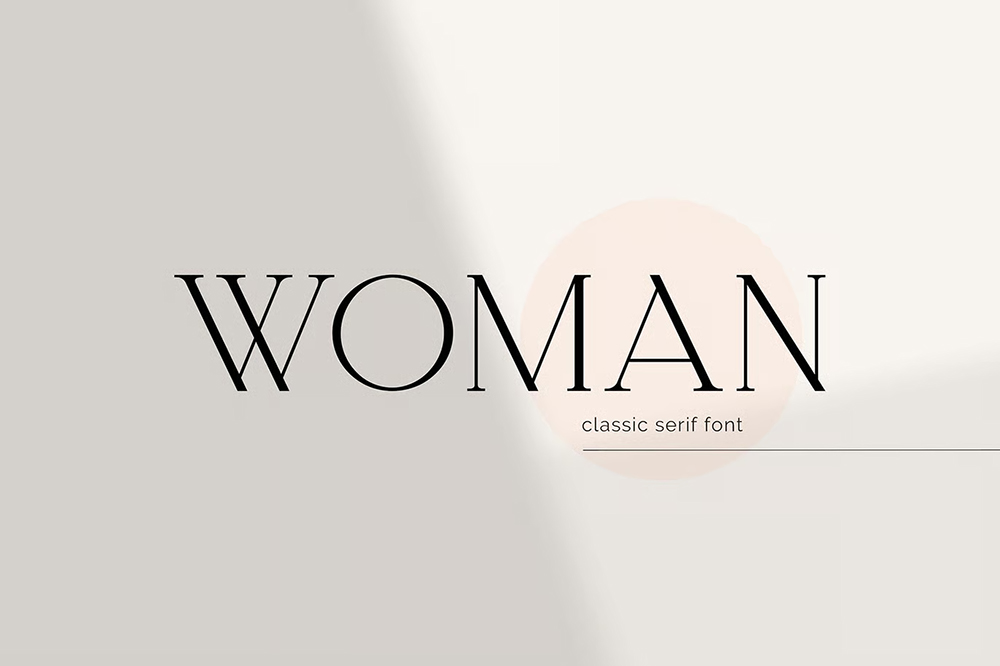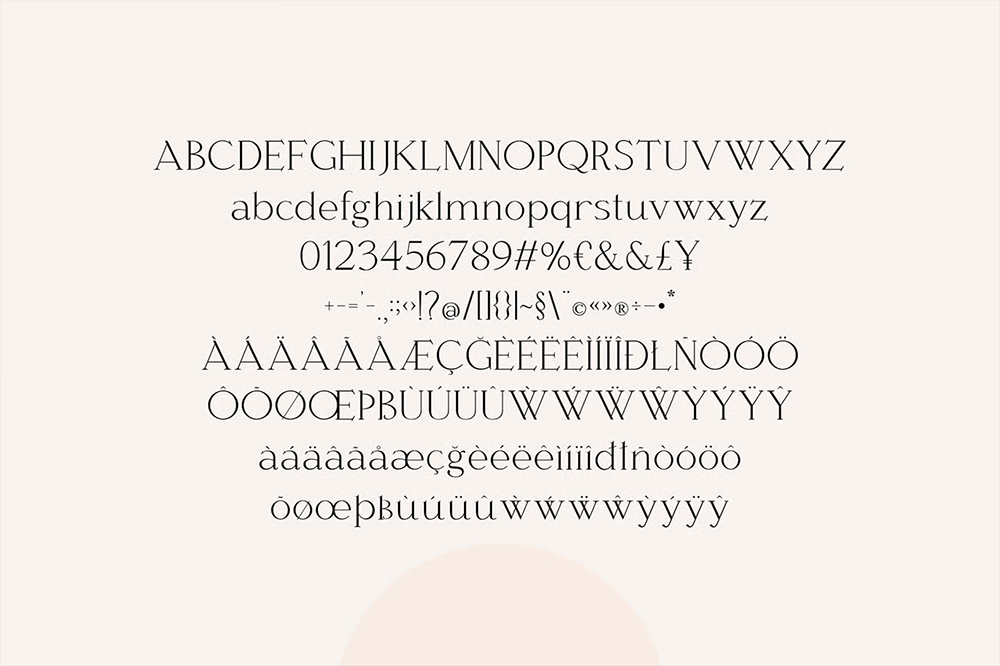
فونت پرمیوم و انگلیسی Woman Font یک فونت سریف مدرن و زیبا است که در هر منحنی، ظرافت و زیبایی را به تصویر میکشد. Woman که برای…
فونت پرمیوم و انگلیسی Woman Font یک فونت سریف مدرن و زیبا است که در هر منحنی، ظرافت و زیبایی را به تصویر میکشد. Woman که برای تلفیق زیبایی جاودانه و ذوق معاصر طراحی شده است، اعتماد به نفس و ظرافت را به نمایش میگذارد و آن را به انتخابی ایدهآل برای برندسازی لوکس، طرحهای سرمقالهای، پروژههای مد و بستهبندی شیک محصولات تبدیل میکند. Woman با فرمهای حروف تمیز، لیگاتورهای منحصر به فرد و تضاد ملایم بین خطوط ضخیم و نازک، لمسی از ظرافت و حرفهایگری مدرن را به هر هویت بصری اضافه میکند. چه برای لوگو، مجله، دعوتنامه یا طرحهای رسانههای اجتماعی استفاده شود، Woman پروژه شما را با حس کلاس و زنانگی ارتقا میدهد.